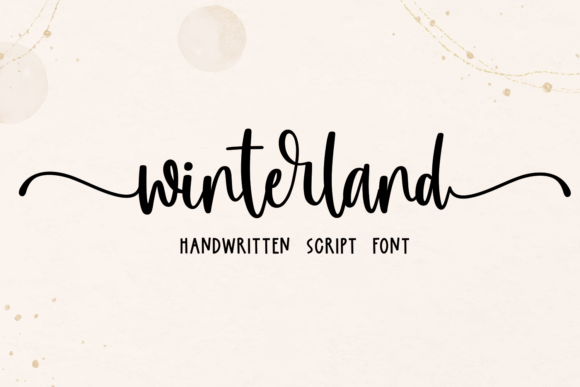
Winterland
Việc tìm kiếm các thành phần thiết kế phù hợp có thể là một thách thức, nhưng Winterland cung cấp một bộ sưu tập đặc biệt giúp nâng tầm công việc của bạn ngay lập tức.
Được chế tác với độ chính xác cao, Winterland cung cấp các vector sạch, kiểu chữ mượt mà và giấy phép thương mại để bạn yên tâm.